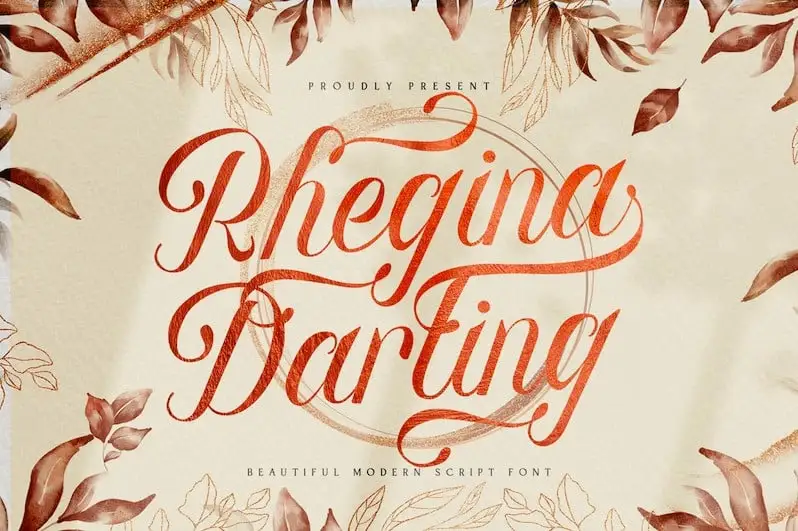
Rhegina Darling Calligraphy Font – Download Grátis
A Rhegina Darling Calligraphy Font é uma herança moderna da arte do desenho a mão feminino. Desenhada pelo talentoso designer GoldenGraph Design, esta fonte traz aos seus projetos um toque de elegância e delicadeza que se adequam perfeitamente para criações em estilo calligrafia moderno. Com sua variedade inovadora de traços inicias e finais, Rhegina Darling é fácil de usar e aplicar em qualquer projeto, seja ele editorial ou gráfico digital. O design oferece uma vasta gama de características que incluem um conjunto completo de letras maiúsculas e minúsculas, pontuação diversificada, números e suporte multilíngue. O grande diferencial desta fonte é a sua integração com opções estilizadas do Set Estilístico capazes de atender aos mais exigentes criadores digitais que utilizam software OpenType (como Photoshop, Illustrator ou InDesign), garantindo um resultado superior em qualquer projeto gráfico. Esta font é perfeita para designers que buscam uma arte feminina na modernidade. Ela não apenas oferece um acabamento elegante e refinado para sua produção de design, mas também permite uma personalização única e um toque diferenciador aos seus projetos. Seja você criando um livro editorial sofisticado ou desenvolvendo a identidade visual de uma marca, Rhegina Darling traz o seu jeito único e autêntico à mesa.